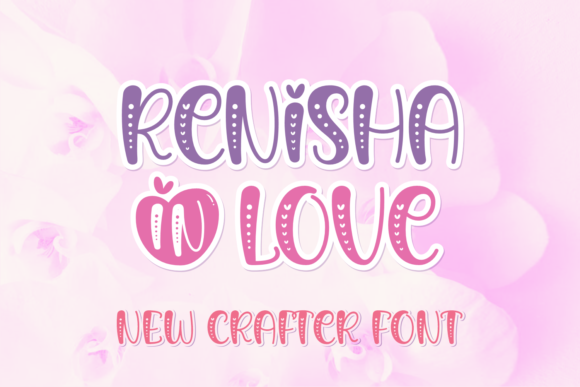
Creativefabrica Renisha in Love Font
[Creativefabrica] Renisha in Love Font
Renisha in Love - это причудливый шрифт с расслабляющей темой, отличающийся прекрасным стилем.
Независимо от темы, этот шрифт будет невероятно полезным для библиотеки ваших шрифтов, так как он способен возвысить любое творение.